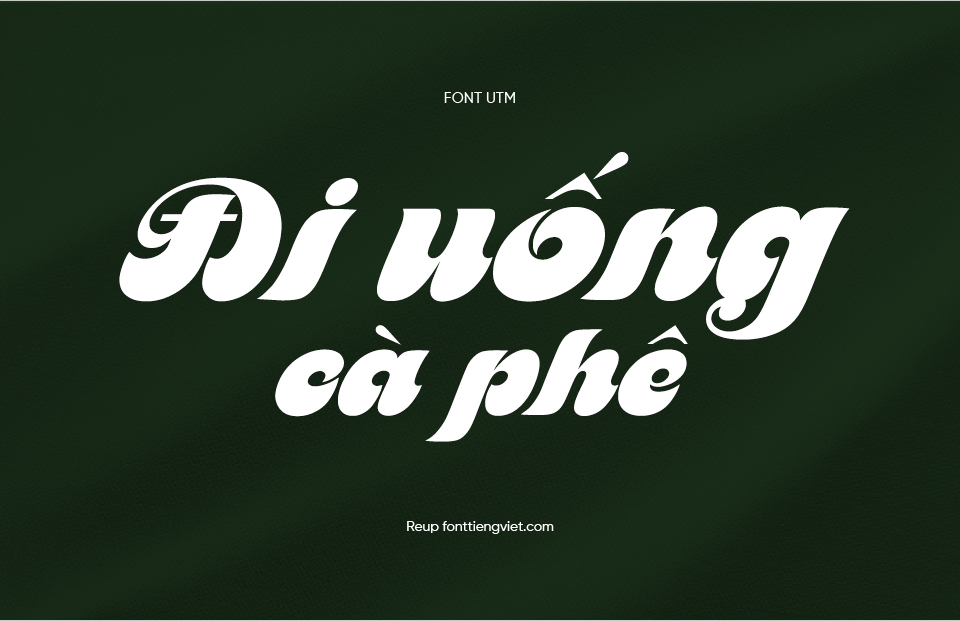
Font Việt hóa UTM Mother: Lựa chọn tinh tế cho thiết kế hiện đại
Giới thiệu về Font Việt hóa UTM Mother
Trong thế giới đồ họa, việc tìm kiếm một bộ Font Chữ vừa mang nét cổ điển vừa giữ được sự thanh thoát hiện đại là điều không hề dễ dàng. Font Việt hóa UTM Mother chính là giải pháp hoàn hảo dành cho những ai yêu thích sự mềm mại nhưng vẫn đầy cá tính. Đây là một phông chữ script được thiết kế tỉ mỉ, giúp truyền tải cảm xúc một cách chân thực nhất qua từng nét bút. Với phiên bản đã được việt hóa hoàn chỉnh, các nhà thiết kế tại Việt Nam có thể dễ dàng sử dụng các dấu tiếng Việt mà không lo lỗi hiển thị, từ đó tạo ra những tác phẩm nghệ thuật chỉn chu và chuyên nghiệp hơn trong các dự án học tập hay làm việc.
Ưu điểm nổi bật của bộ Font Việt hóa UTM Mother
Tính ứng dụng cao trong thiết kế
Font Việt hóa UTM Mother sở hữu những đường nét bay bổng, uốn lượn tự nhiên, cực kỳ phù hợp để thiết kế thiệp mời, bìa sách hoặc các tiêu đề trình chiếu. Đối với các bạn học sinh và giáo viên, phông chữ này giúp các bài thuyết trình trở nên sinh động và thu hút sự chú ý hơn. Ngoài ra, UTM Mother còn được ưa chuộng trong việc tạo ra các mẫu logo mang phong cách nghệ thuật cá nhân hoặc các câu trích dẫn truyền cảm hứng trên mạng xã hội.
Kết luận về bộ Font Việt hóa UTM Mother